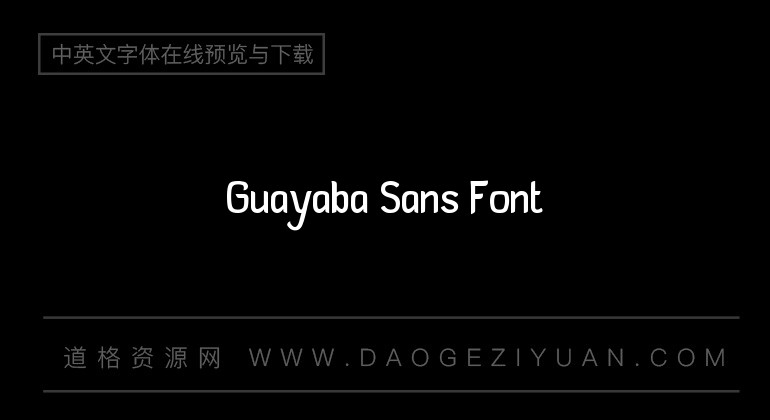
Guayaba Sans Font
Guayaba Sans 是一款现代化的无衬线字体,设计灵感源自拉丁美洲的艺术和文化。它由字体设计师Juan Pablo del Peral于2017年设计,是一种非常适用于品牌设计、海报、标志、标题和印刷设计等领域的字体。 Guayaba Sans 字体的字母形状和间距非常均衡,具有很好的可读性和清晰度。它采用了圆润的形状和柔和的曲线,使它在视觉上非常吸引人。此外, Guayaba Sans 字体还提供了7种不同的字重,可以满足不同设计需求。 总体来说,Guayaba Sans 字体是一款现代化、清晰、易读,并且在视觉上非常吸引人的字体,适用于许多设计领域。
Guayaba Sans Font是一款非常不错的手写艺术字体,具有很好的视觉感,适合于文化类的宣传设计、商业类品牌的广告和产品包装设计以及个性化文字排版等较多场景。